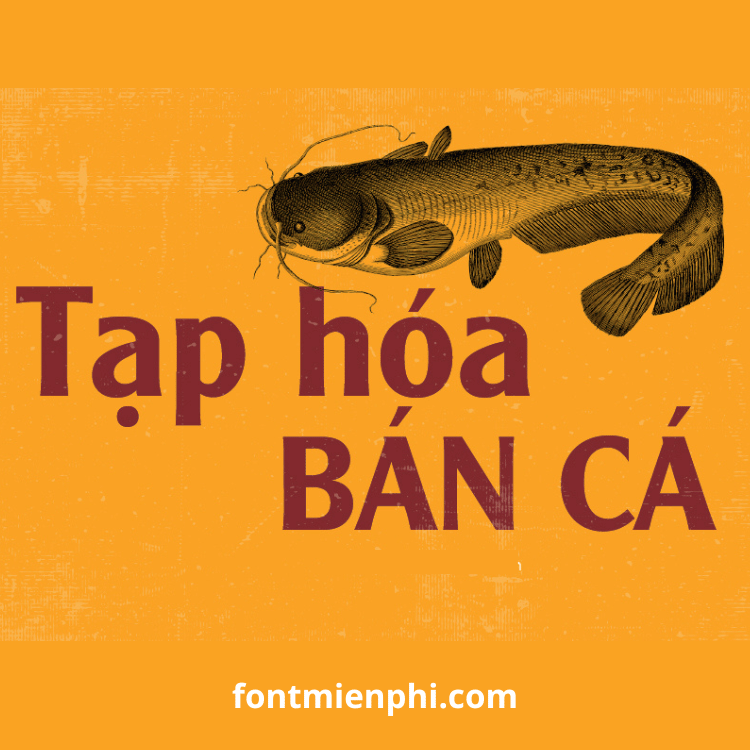
Mô tả font UTM Alexander (Việt hóa):
UTM Alexander là font chữ serif thanh lịch, mang phong cách cổ điển nhưng vẫn hiện đại, với các nét mảnh và độ tương phản nhẹ nhàng. Phiên bản Việt hóa hỗ trợ đầy đủ dấu tiếng Việt, phù hợp cho các thiết kế sang trọng, tinh tế.
Ứng dụng thiết kế Việt hóa font UTM Alexander :
• Thiết kế logo, thương hiệu cao cấp
• Bìa tạp chí, sách, namecard
• Bao bì sản phẩm đẳng cấp
• Poster nghệ thuật, lịch trình sự kiện
• Website, profile công ty
Font phù hợp với phong cách vintage, retro hoặc minimalism, mang lại cảm giác tinh tế và đẳng cấp.